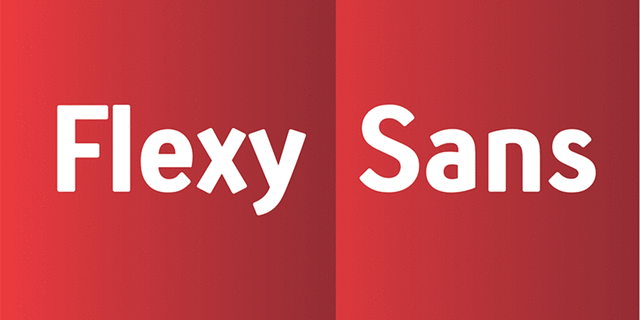
Флекси Санс – отличный и комфортный для восприятия гуманистический гротеск, подходящий как для текста, так и для таблиц и небольших надписей. Разработан Андреем Кудрявцевым в 2011 году.
Ассоциации c семейством Flexy SansКачества и характер:
мягкий, гладкий, доверительный, лаконичный, доступный, комфортный, городской, точный, строгий, современный, универсальный, простой, ровный, техничный, устойчивый, стабильный, статичный, надежный, важный, убедительный